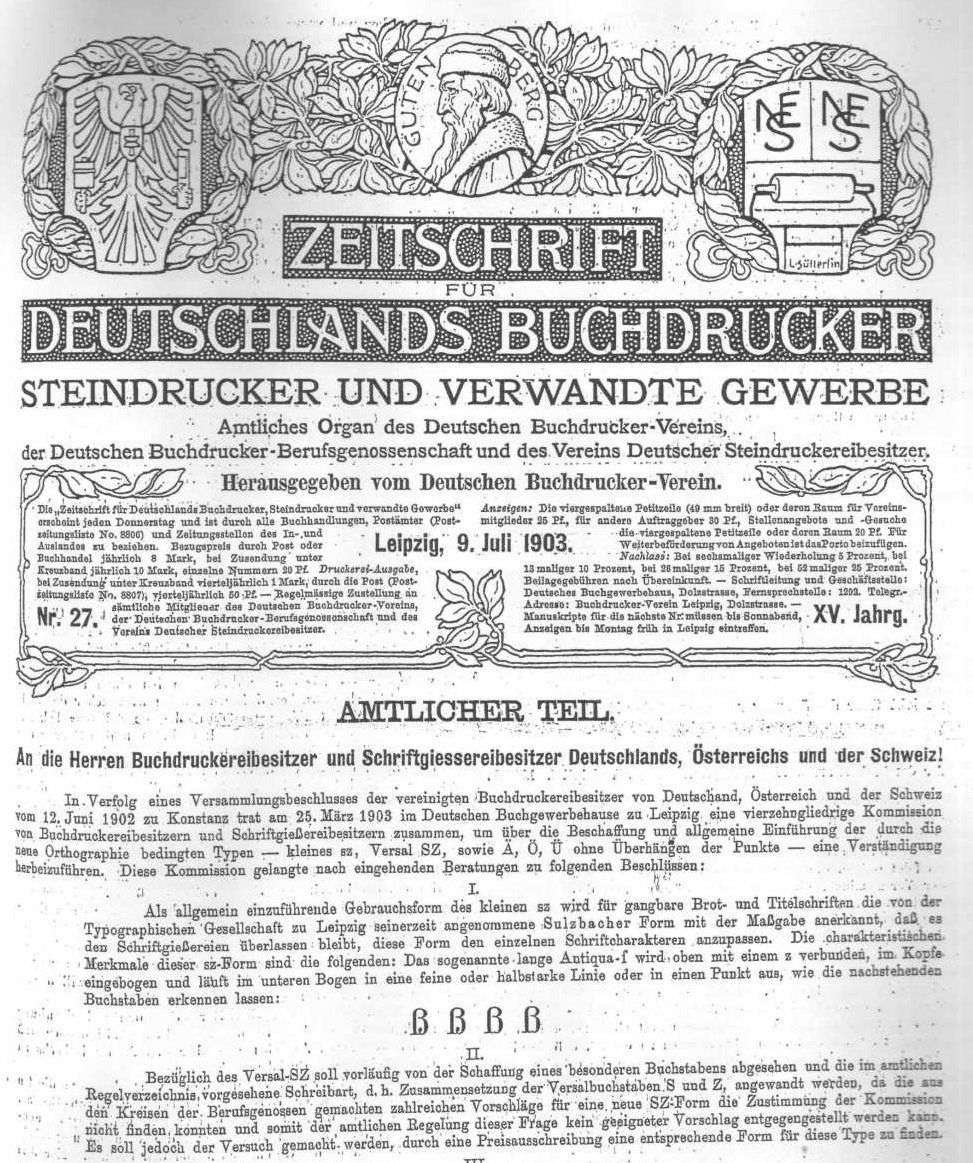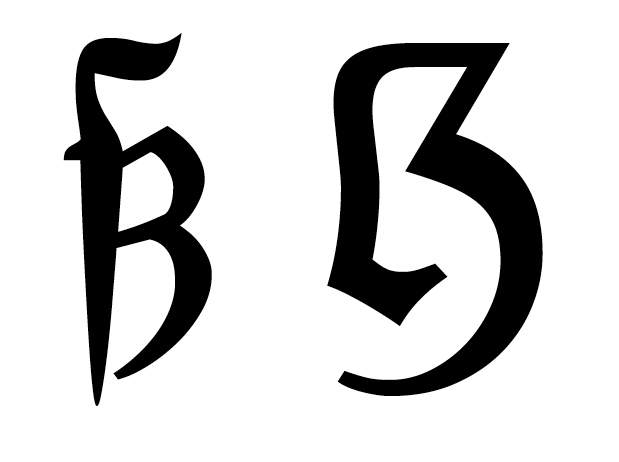
Es kommt mir halt alles etwas gekünstelt vor, vor allem die orthographische Begründung.
a→A→a
b→B→b
ß→ẞ→ß
Was ist daran gekünstelt? Das ist die lateinische Schrift in ureigenster Anwendung.
Gekünstelt wirken eher die Ausflüchte, dass Problem auf Einzelfälle herunterzuspielen eben z.B. auf die Behörden zu schieben statt es an der Wurzel zu packen und das ß wie jeden anderen Buchstaben auch zu benutzen.
Das Grundproblem ist das:
ß→SS→? (ss oder ß)
Lösung:
ß→ẞ→ß
Das wird sich nie ändern, egal wie Behörden Namen erfassen oder ob Online-Banking mal auf Unicode umgestellt wird. Solange es Versal-Satz und ß gibt, wird das fehlende ẞ Probleme machen. Da kann man noch so lange an den Symptomen rumdoktern.
Die Familie von eine Bekannte von mir ist mal vor lange, lange Zeit als Vos von Holland nach Deutschland gezogen. Die Deutsche Behörden machten daraus Voß. Weil die Deutschen Vos sonst als „Voos“ aussprechen würde. Und in Holland ist „voos“ etwas unanständiges.
Das klingt aber eher nach Wunsch der Namensträgerin als nach Anordnung der Behörde, denn der dürfte die Aussprache ziemlich schnuppe sein ... Sonst müsste der niedersächsische Ministerpräsident Mäckällister geschrieben werden ... ;-)
Nach der Rückwanderung in Holland bestanden die holländische Behörden auf Vosz mit der Begründung, dass es in Holland kein ß gäbe und das Zeichen nun mal sz heißt.
Spätestens dann hätte ich ja mit der niederländischen Geburtsurkunde gewedelt oder ersatzweise mit dem deutschen Duden, je nachdem, ob Vos oder Voss der Zielname gewesen wäre ... Letzterer eignet sich beim erfolglosen Wedeln auch zum um-die-Ohren-schlagen ... ;-)
a) alle nationalen behörden eine einheitliche schreibweise eintrichtern kann.
b) oder es doch einfacher ist ein eszett für den versalsatz zu entwerfen
Man sollte in der Tat den Behörden mal abgewöhnen, in Dokumenten wie Ausweisen die Versalschreibweise zu verwenden, denn ganz unabhängig vom [sZ][/sZ] gibt es ja bspw. auch noch andere, nicht eindeutig rückführbare Namen wie MACDONALD.
Und auch, wenn man bei mir die Rückübersetzung meistens hinkriegen sollte, heiße ich ja eigentlich auch nicht JACOBS, sondern Jacobs ... Im übrigen finde ich, dass eine gewisse Kaffeefirma mal besseres Marketing machen sollte, damit auch mal die Jakobse erklärungsbedürftig werden ... ;-)
Das klingt aber eher nach Wunsch der Namensträgerin als nach Anordnung der Behörde, denn der dürfte die Aussprache ziemlich schnuppe sein
Das hat sich wohl aus dem Gespräch des Antragstellers (A) und Beamten (B) wohl in etwa so ergeben:
B: »Name?«
A: »Vos«
B: »Schreiben Sie den Namen als V, o, s, s oder als V, o, ß?
A: »Nein, als Vos, mit einem s«
B: »Das spricht sich aber als Voos, ist Ihnen das klar?«
A: »Nein, das habe ich nicht gewusst* was kann man da machen?«
B: …
*das sagen normalerweise eigentlich nur Deutsche, jedoch in einem anderen Zusammenhang ;–)
Spätestens dann hätte ich ja mit der niederländischen Geburtsurkunde gewedelt
Die Geburtsurkunde war ja Deutsch …
Ich sehe das als direkt Betroffener (der Nachname lautet Weiß) entspannter, weil ich es gewohnt bin, dass mein Name irgendwie so geschrieben wird, dass am Ende Weiß rauskommen. In CH und dem Ausland Weiss, in Versalen WEISS, in D gemischt Weiß …
Ralfs Argumentation a→A→a, b→B→b, …, ß→ẞ→ß kann ich zwar nachvollziehen und finde sie auch schön logisch, sie ist aber noch nicht mal für die deutschsprachigen Gebiete gültig (siehe Weiss in CH), sondern rein auf Deutschland und Österreich beschränkt. Das ist für mich einfach heutzutage ein k.o.-Kriterium.
Wie gesagt: die Eigennamen-Schreibung ist nur EIN Symptom des Problems, dass ein lateinischen Buchstaben nicht in beiden Häusern vorhanden ist. Es wird der Sache nicht gerecht, sich daran zu verbeißen und Abhilfe oder das Sich-damit-abfinden nur auf diesen Fall anzuwenden.
Ich weiß, wir drehen uns im Kreis und im Grunde sind alle Argumente dafür und dagegen wiederholt genannt. Ändert aber nichts an der Tatsache, dass die einen das ẞ für notwendig erachte und die anderen nicht.
Was aber speziell bei meinem (und sicher auch anderen) Namen dazukommt: Ich möchte in CH und im Ausland nicht WEIB genannt werden, weil WEIẞ keiner kennt und die Ähnlichkeit zwischen ẞ und B je nach Schriftart viel zu groß ist.
Wenn die Argumente aber auf sachlich richtigen Tatsachen beruhen (Verwechslung mit B im Ausland, Nichtvorhandensein von ß und ẞ im Ausland etc.) haben beide recht. Dann wird es wieder Glaubenssache, was besser ist ;-)
Wie gesagt: die Eigennamen-Schreibung ist nur EIN Symptom des Problems, dass ein lateinischen Buchstaben nicht in beiden Häusern vorhanden ist.
In der Tat. Das [sZ][/sZ] ist, spätestens seitdem das ß eine eindeutige orthographische Bedeutung bekam, einfach sinnvoll.
Das hat sich wohl aus dem Gespräch des Antragstellers (A) und Beamten (B) wohl in etwa so ergeben:
Vermutlich ... ;-) Aber jedenfalls keine behördliche Zwangsanordnung des ß
gefällt mir auch gut. Weil ich es ein wenig problematisch finde wenn der große Bruder ein Abklatsch der kleinen Schwester ist. Soll schon seinen eigenen Charakter bekommen.
Oh, da sehe ich doch irgendwie ein kleines Problem: VERSALIEN haben doch gar keine Unterlängen!!! Gruß Ottl
Versalien haben keine Unterlängen? Q, J …
Nicht immer. Das J hat selten eine, beim Q ist sie optisch oft sehr gering ausgeprägt. Ist also durchaus ein Argument gegen die Unterläge beim Versal-ß.